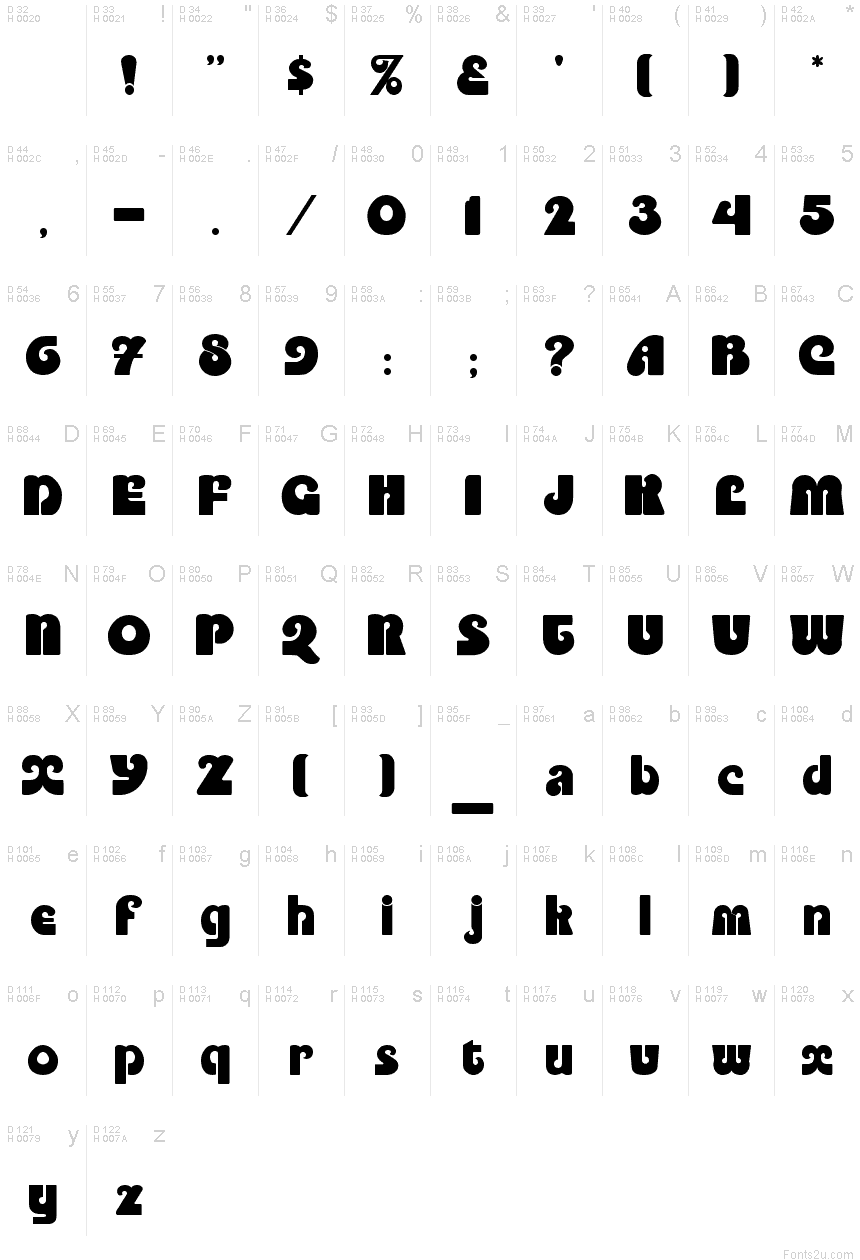
Saltire è un font display gratuito e dal sapore groovy, capace di trasformare curve massicce in un ritmo audace e vivace. Le sue lettere larghe e morbide, insieme agli occhielli stretti e profondi, danno quasi l'idea di una scultura, come se fossero modellate nel vinile o tracciate con inchiostro fluido. Il mix tra forme arrotondate e verticali dritte crea una silhouette originale che cattura l'attenzione, risultando divertente e rétro senza mai apparire disordinata.
Con Saltire, i titoli su poster, volantini musicali, packaging di snack, branding rétro, miniature e loghi creativi attirano subito lo sguardo. Questo font gratuito brilla nelle grandi dimensioni, dove i suoi tratti spessi e le curve generose possono davvero respirare; abbinalo a un semplice sans serif geometrico per il testo principale, lasciando che sia Saltire a dettare lo stile, mentre il resto rimane pulito e discreto.